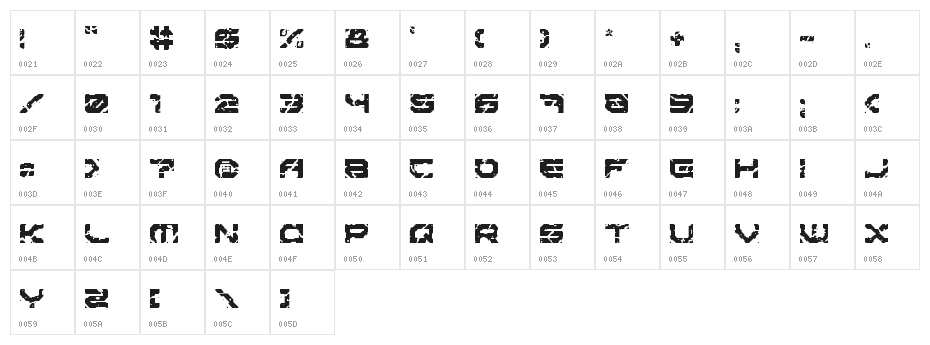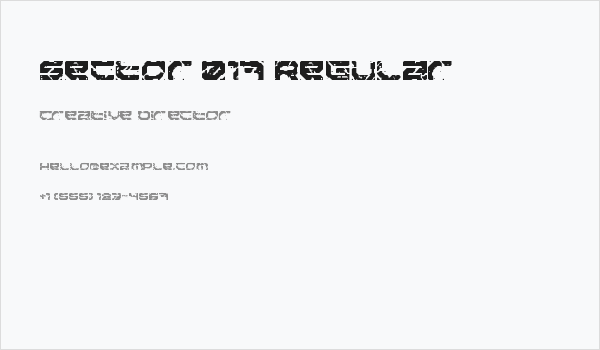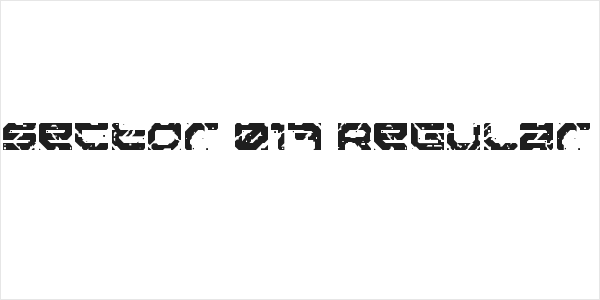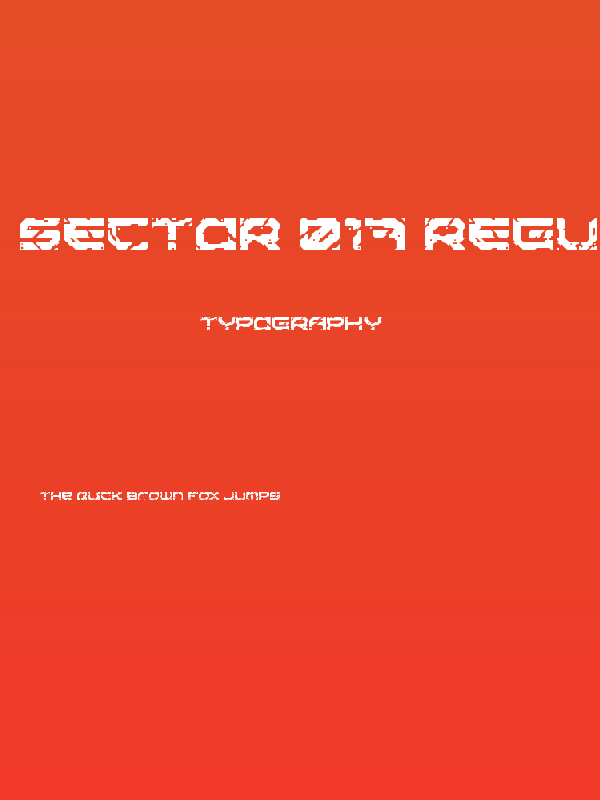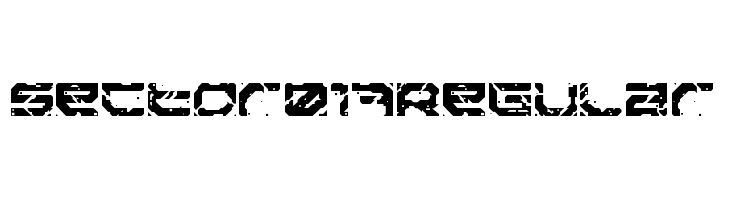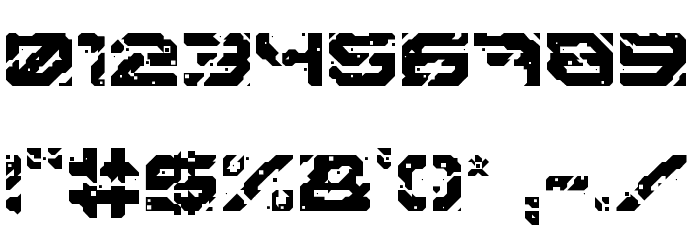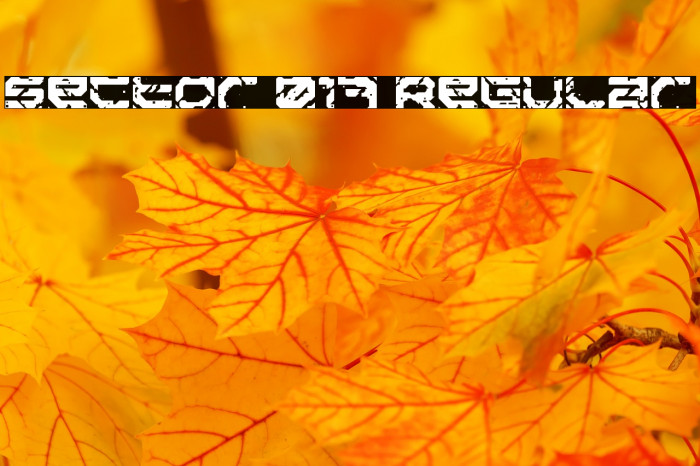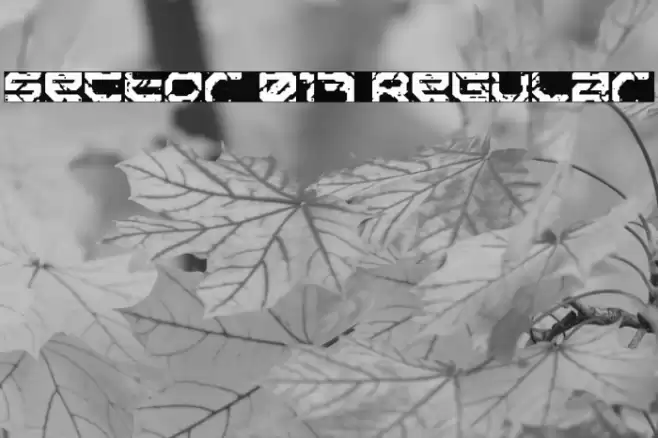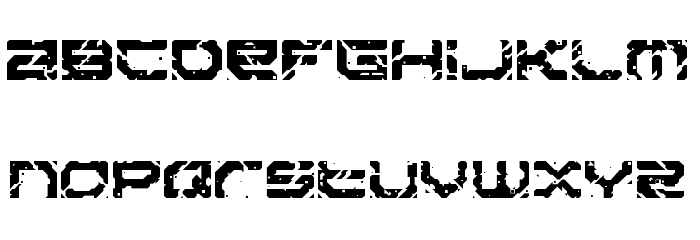
Sector 017 Regular Font
✎ Stencil
| Categorii | Stencil |
| Stil general | Futuristic, Distressed |
| Proiecte propuse | Ideal for sci-fi themed projects, video game titles, posters, and branding that requires a modern, edgy look. |